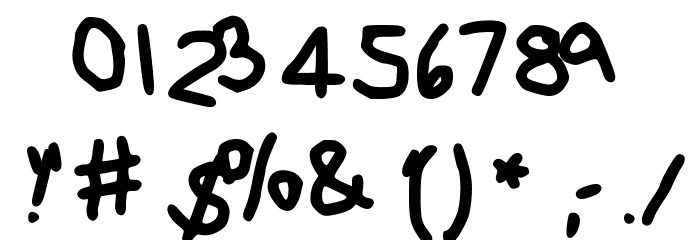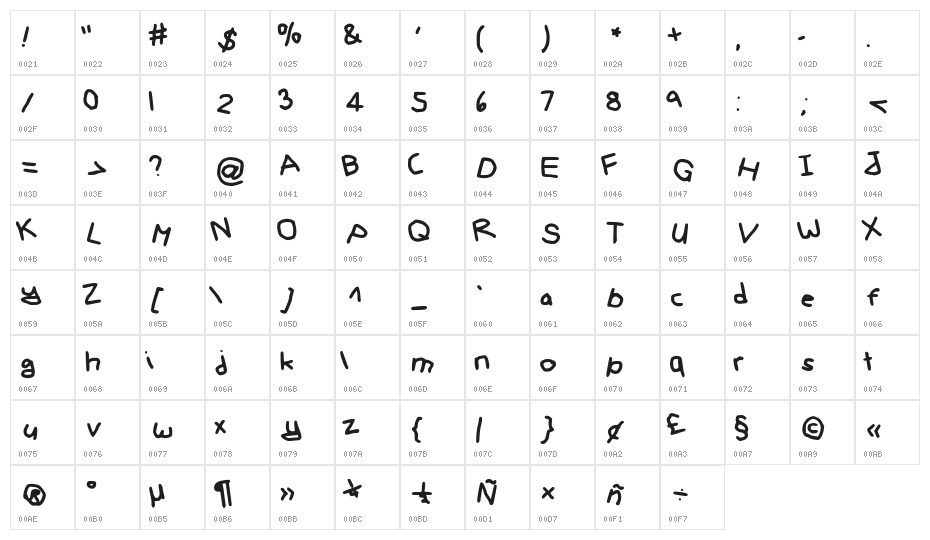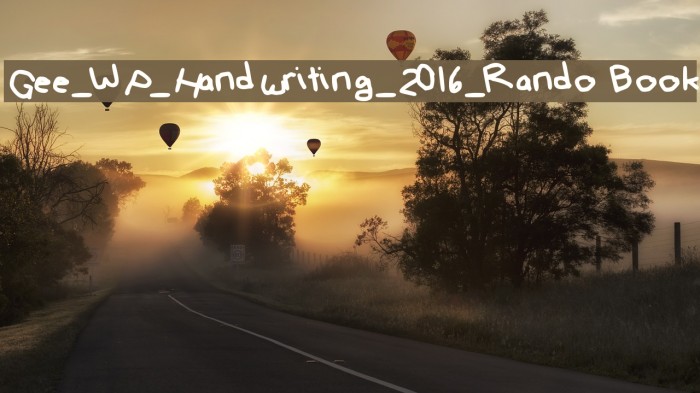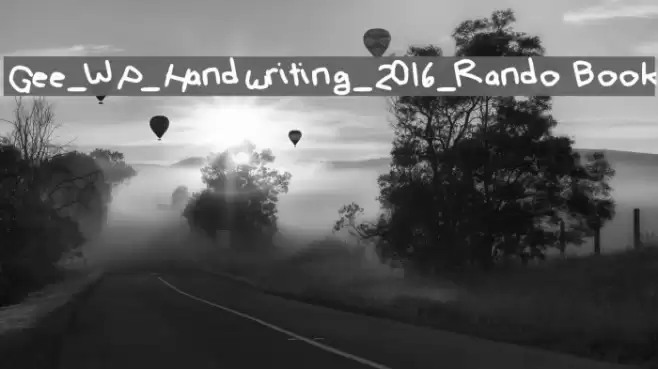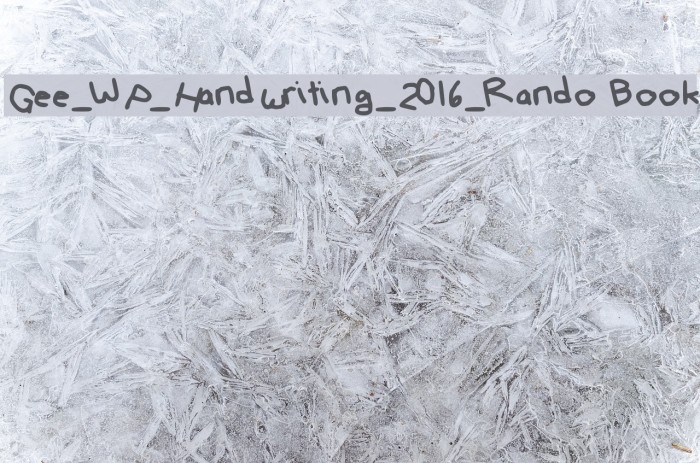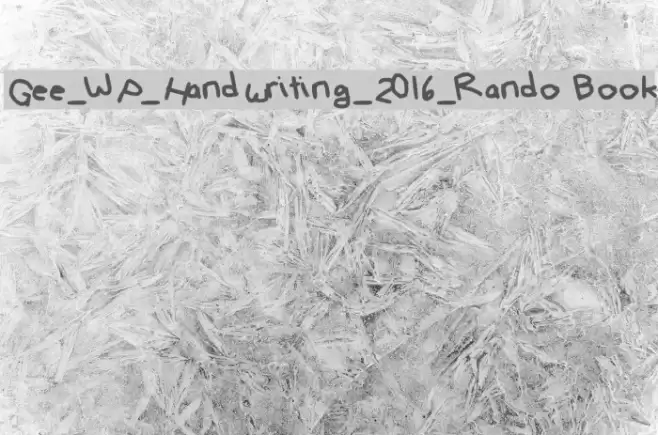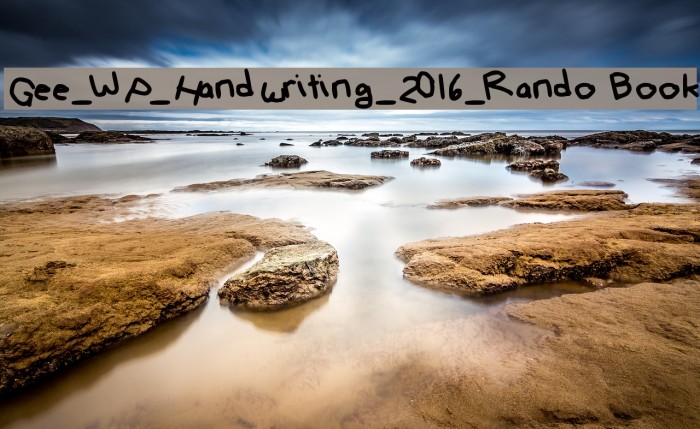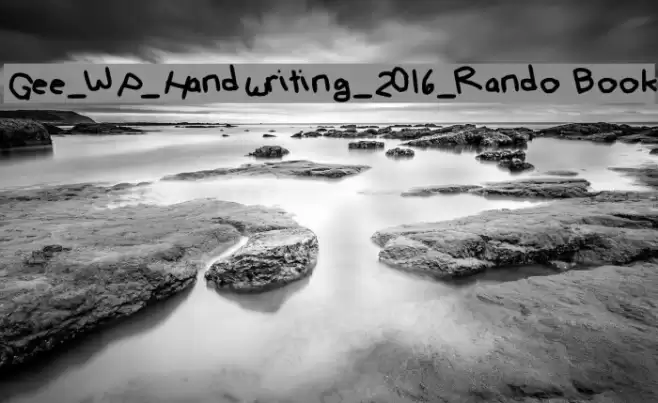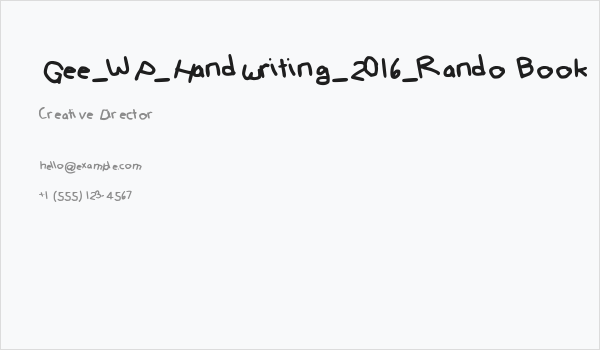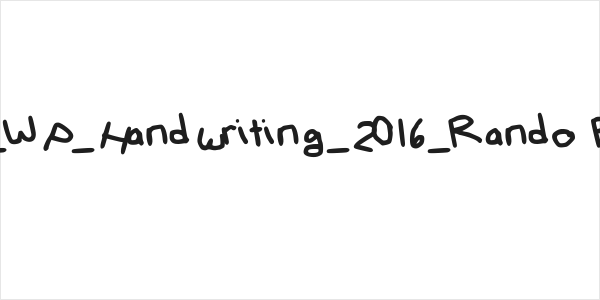
Gee_WP_Handwriting_2016_Rando Book Font
| Gesamtstil | Casual, Playful |
| Anwendungsfall | Headlines, Informal text, Creative projects |
| Vorgeschlagene Projekte | Ideal for children's books, greeting cards, personal blogs, and informal branding. |